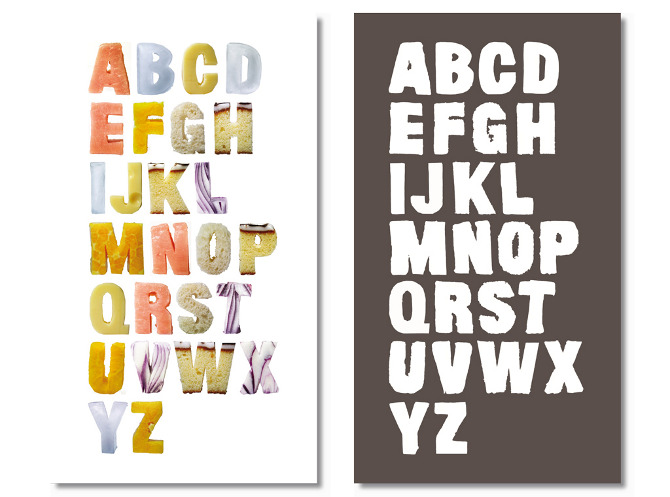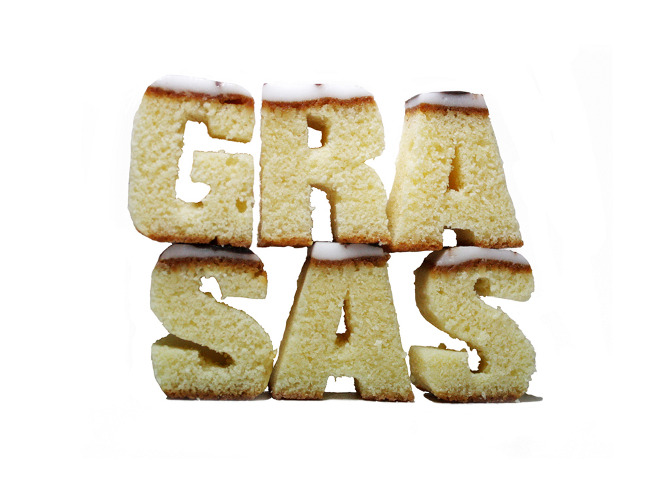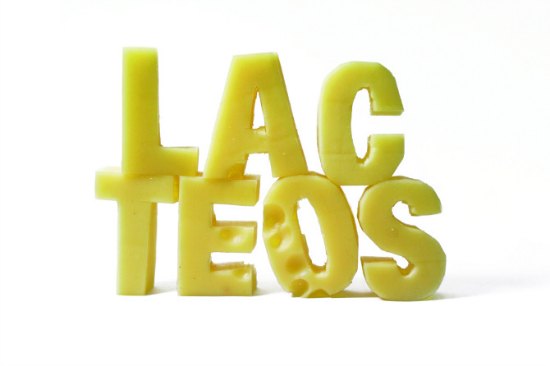
Ayer nos llegó por mail esta joyita que no podíamos dejar de compartir con vosotros. Y es que si hay algo que nos guste más que las tipografías son las tipografía que se comen. De eso trata este proyecto de Nuria Brigue, que creó estas palabras recortadas en alimentos para realizar las portadas de unos libros sobre alimentación sana. No digáis que no entran ganas de hincarle el diente…
Tipografías que se comen